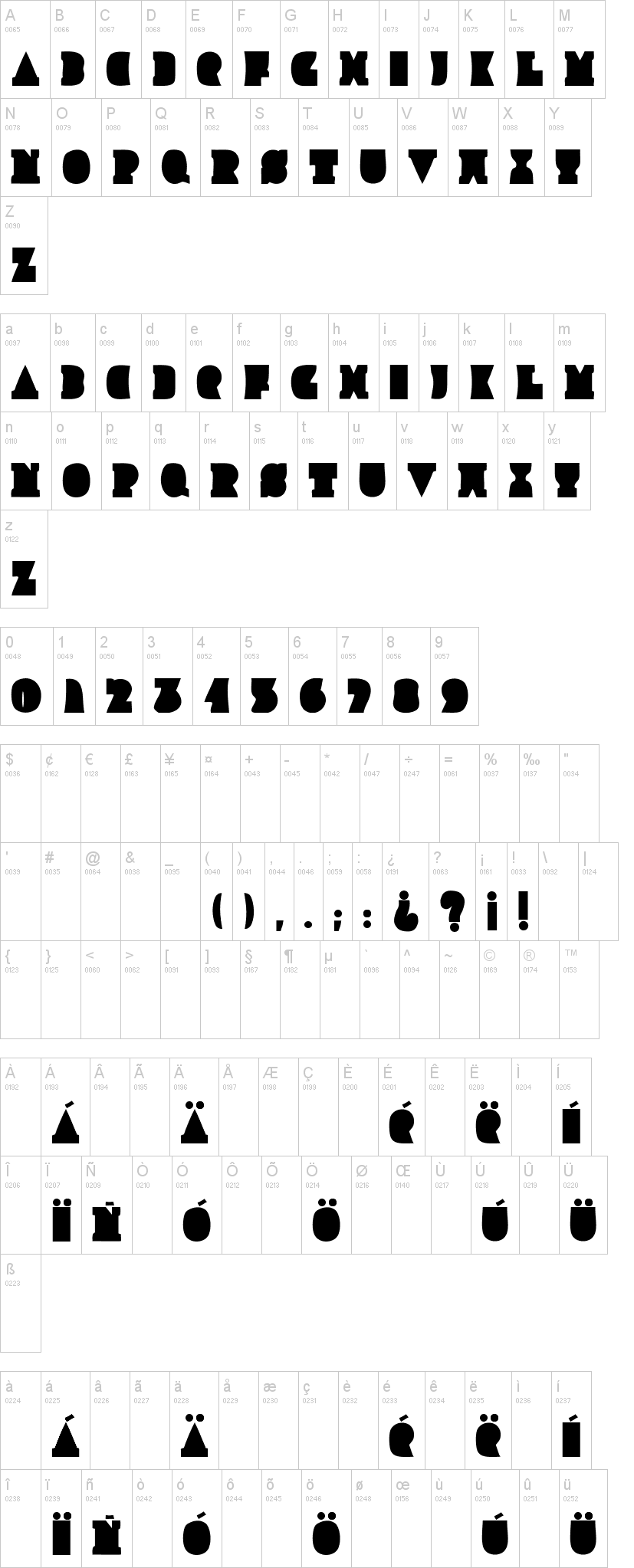
Шрифт Improlija
Improlija es una tipografía inspirada de la "Jersey Serif Typeface" creada por el estudio Fontan2. Me tomé el atrevimiento de retocarla a mano y de agregarle caracteres del español y símbolos que no tenían.